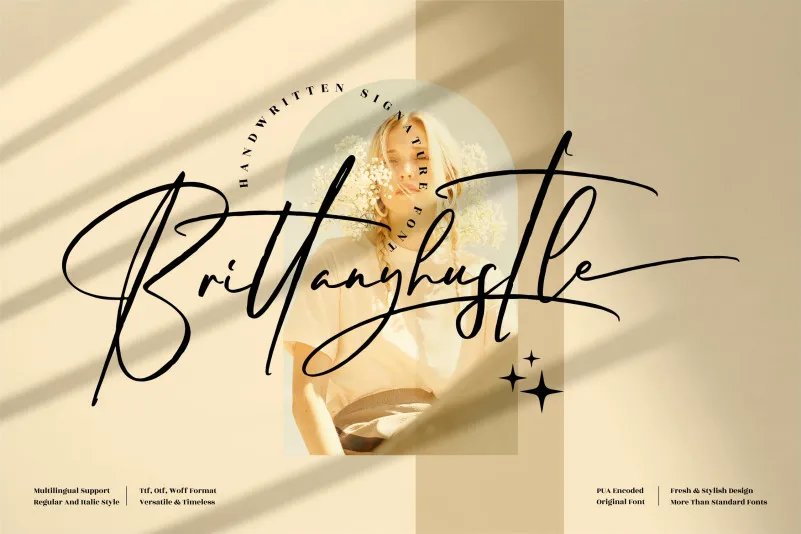
Brittanyhustle Font – Fonte Grátis
Brittanyhustle Font
Esta é uma fonte assinatura premium projetada para os mais variados projetos, desde logotipos até invitations, passando por capas de livros e até mesmo etiquetas de embalagens. A Brittanyhustle Font é perfeita para adicionar um toque sofisticado a qualquer projeto que você possa imaginar. Seja para revestir objetos da vida cotidiana como chávenas ou sacolas, criar mugs personalizados com frases inspiradoras ou até mesmo customizar sua própria foto de maneira única – essa fonte oferece o acabamento elegante e exclusivo que seu projeto merece. Não importa qual seja o tipo de projeto em que você está trabalhando, a Brittanyhustle Font certamente encaixa-se perfeitamente, garantindo uma experiência única e premium para cada criação.